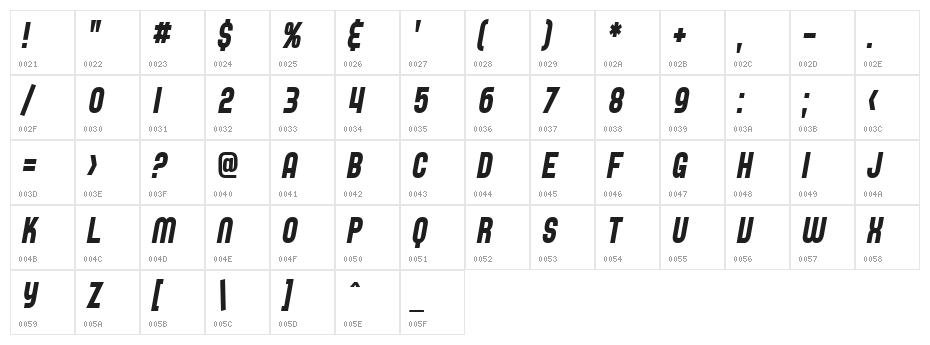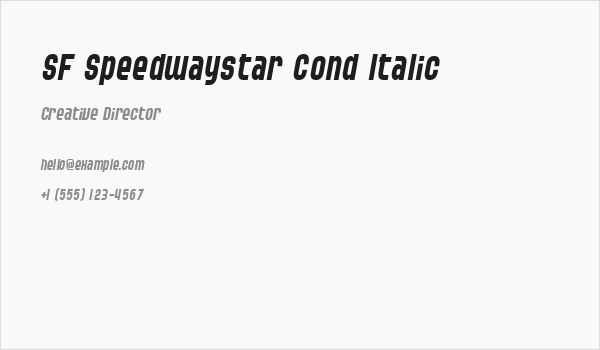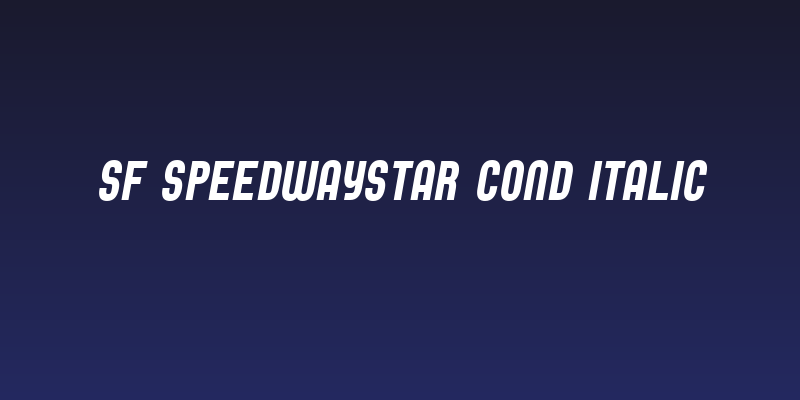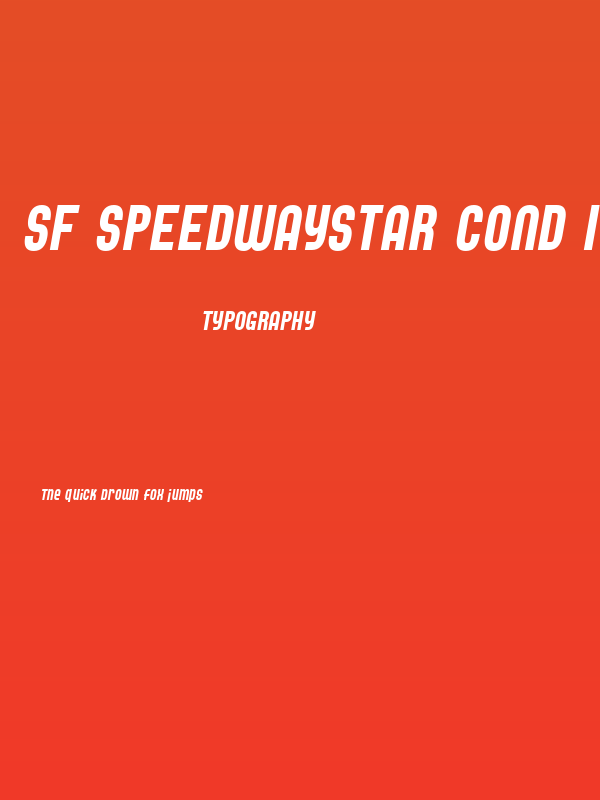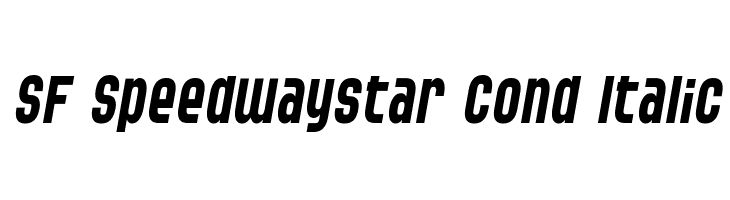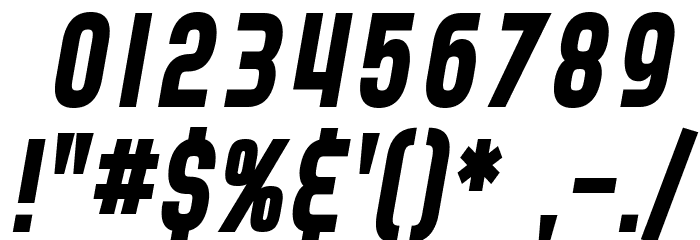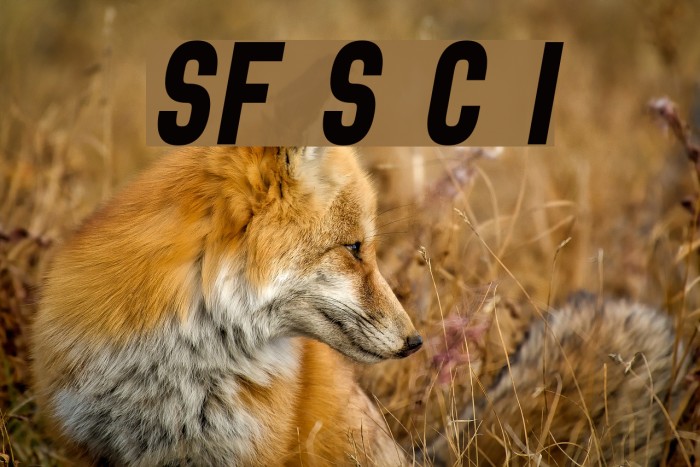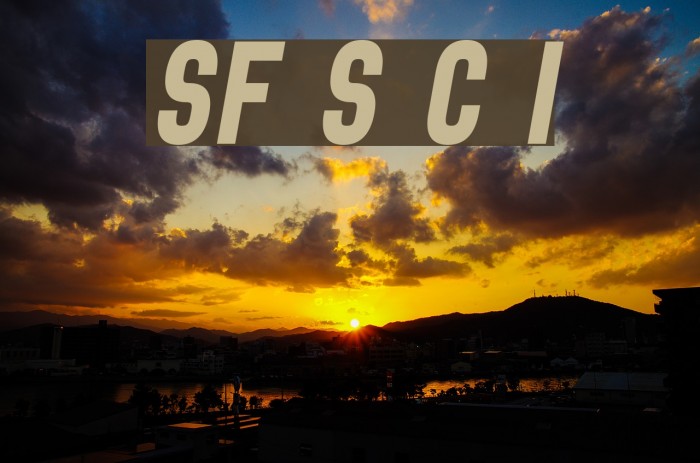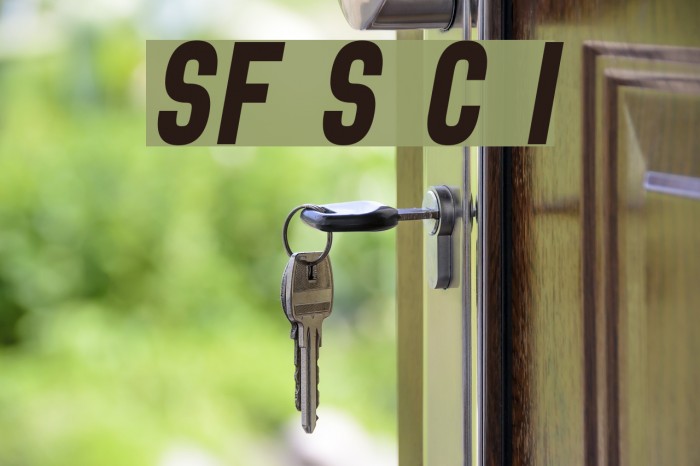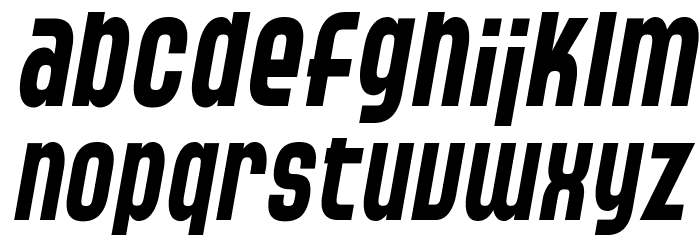
SF Speedwaystar Cond Italic Font
| Progetti proposti | Ideal for sports branding, automotive advertisements, dynamic posters, and any project needing a sense of speed and energy. |